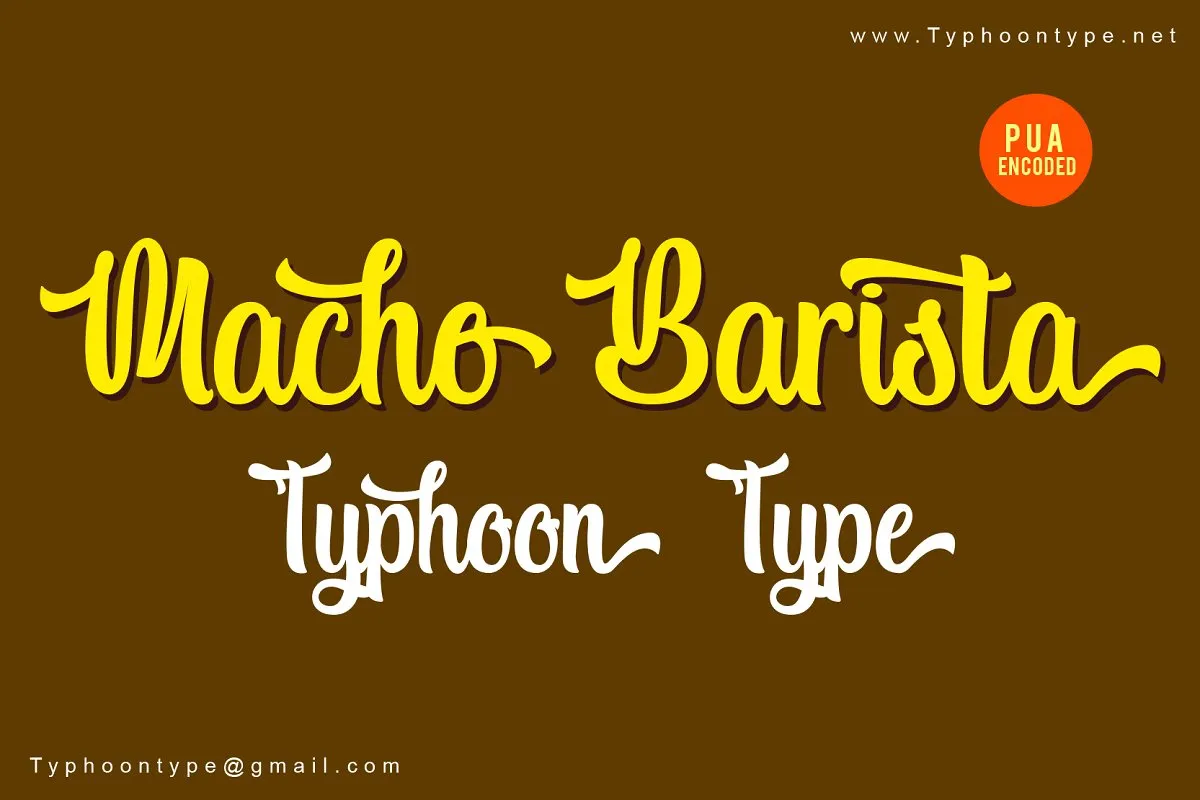
Macho Barista Script Font – Download Grátis
Este é um script font com movimentos fortes e naturais, perfeito para seus projetos incríveis. Ideal para cartões de saudação, branding, desenho de estaçãoamento, mídia social, embalagens, layouts de revistas e impressão em geral. A Macho Barista foi criada pela TyphoonType – S. Srisopha, com uma escrita delicadamente elaborada que é inegavelmente marcante e autêntica. Este font tem tudo o que você precisa para tornar seus designs únicos e impactantes, seja em cartões de aniversário ou em embalagens de produtos. Com o Macho Barista, você terá um recurso indispensável em sua coleção de fonts para aprimorar qualquer projeto gráfico. Este font é especialmente adaptado para cartas de cumprimentos, embalagens de produtos e até mesmo para mídias sociais, oferecendo uma personalização única e imediatamente reconhecível. Adquira já a Macho Barista Script Font e faça suas criações se destacarem ainda mais. Esta font é perfeita para quem busca um toque diferenciado em qualquer projeto gráfico que esteja criando.